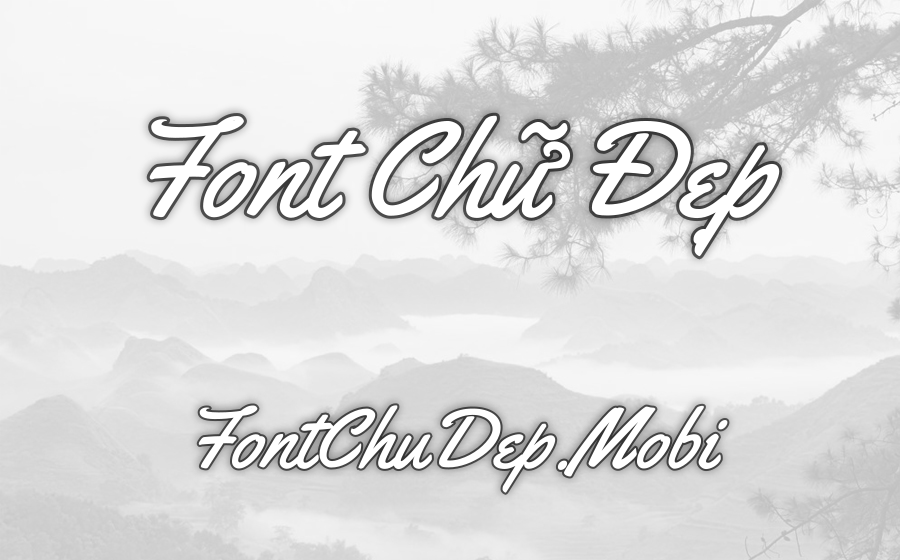
Font LNTH Yellowtail Việt Hóa
LNTH Yellowtail
Yellowtail là một font chữ mà tôi thực sự ấn tượng nhờ vẻ đẹp cổ điển đầy tinh tế của phong cách viết tay. Lấy cảm hứng từ kiểu chữ script Mỹ thập niên 1930, font chữ này thu hút bởi những đường nét uyển chuyển, mềm mại, làm cho người ta liên tưởng đến một thời kỳ hoài cổ nhưng lại không mất đi sự hiện đại. Thật đáng kinh ngạc khi nó phù hợp với các thiết kế vintage, retro và cả trong việc xây dựng thương hiệu chuyên nghiệp.
Phiên bản Việt hóa của Yellowtail, do LNTH thực hiện, đã mở rộng khả năng sử dụng với hỗ trợ tiếng Việt và hơn 50 ngôn ngữ khác. Điều này thực sự tiện lợi cho các nhà thiết kế có nhu cầu làm việc trên phạm vi quốc tế. Tôi tìm thấy font này thông qua FontChuDep.mobi, nơi tập hợp những font chữ đầy thanh lịch và mềm mại, là một lựa chọn không thể tuyệt vời hơn cho các nhà thiết kế đang tìm kiếm một font script độc đáo.
Điểm nổi bật về thiết kế của Yellowtail là độ dày vừa phải cùng với các nét cong mượt mà, tạo nên cảm giác tự nhiên và linh hoạt như bút pháp của một người nghệ sĩ. Nhờ vào sự thanh thoát này, nó được ứng dụng cực kỳ hiệu quả trong các lĩnh vực như thương hiệu, quảng cáo, bao bì sản phẩm, thiệp cưới hay bất kỳ nội dung sáng tạo nào khác.
Sự phổ biến của font Yellowtail là không có gì ngạc nhiên. Nó thường xuyên hiện diện trong các sự kiện như lễ tình nhân, thiệp cưới, và những thiết kế mang phong cách cổ điển. Font này không chỉ giới hạn trong bất kỳ ngành nghề cụ thể nào, mà còn mở rộng khả năng ứng dụng trong quảng cáo, thiết kế thương hiệu, ngành spa, ẩm thực và lĩnh vực in ấn sáng tạo.